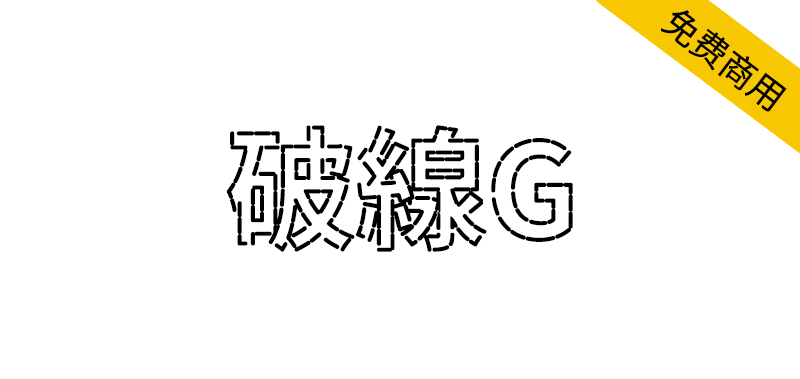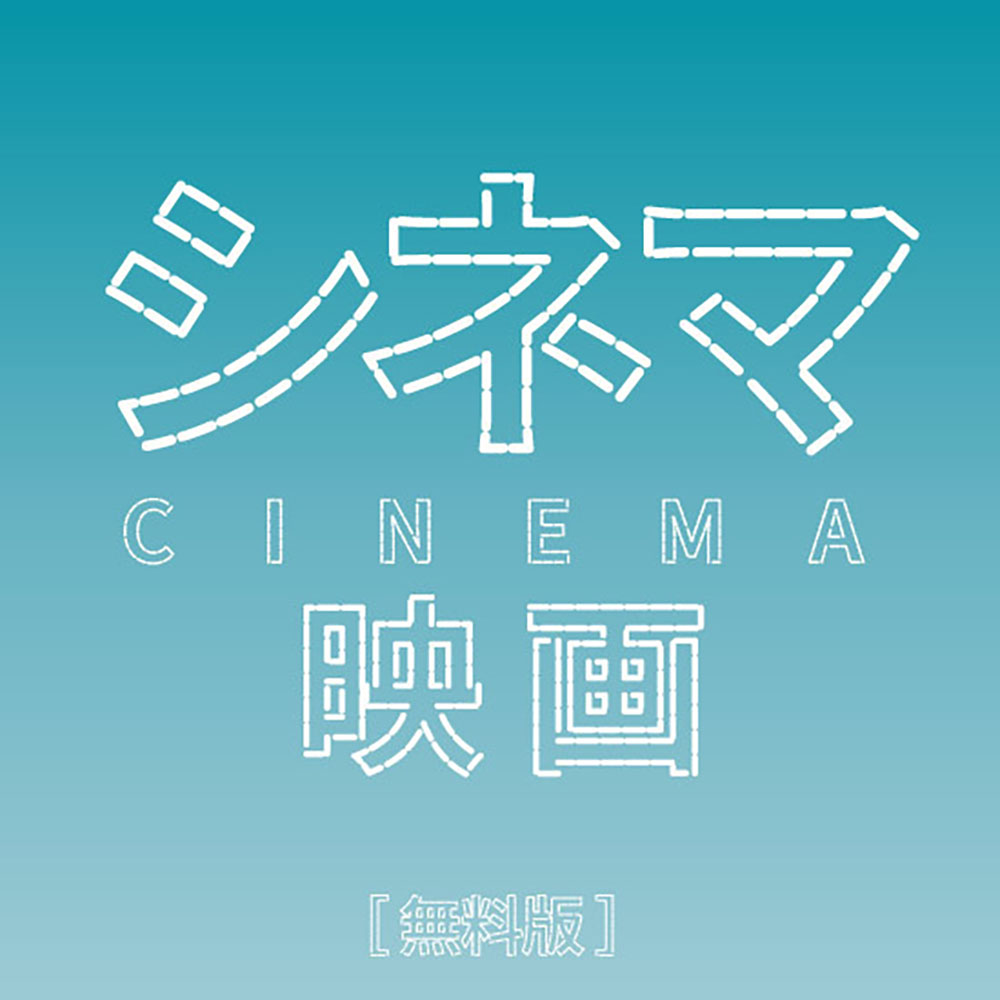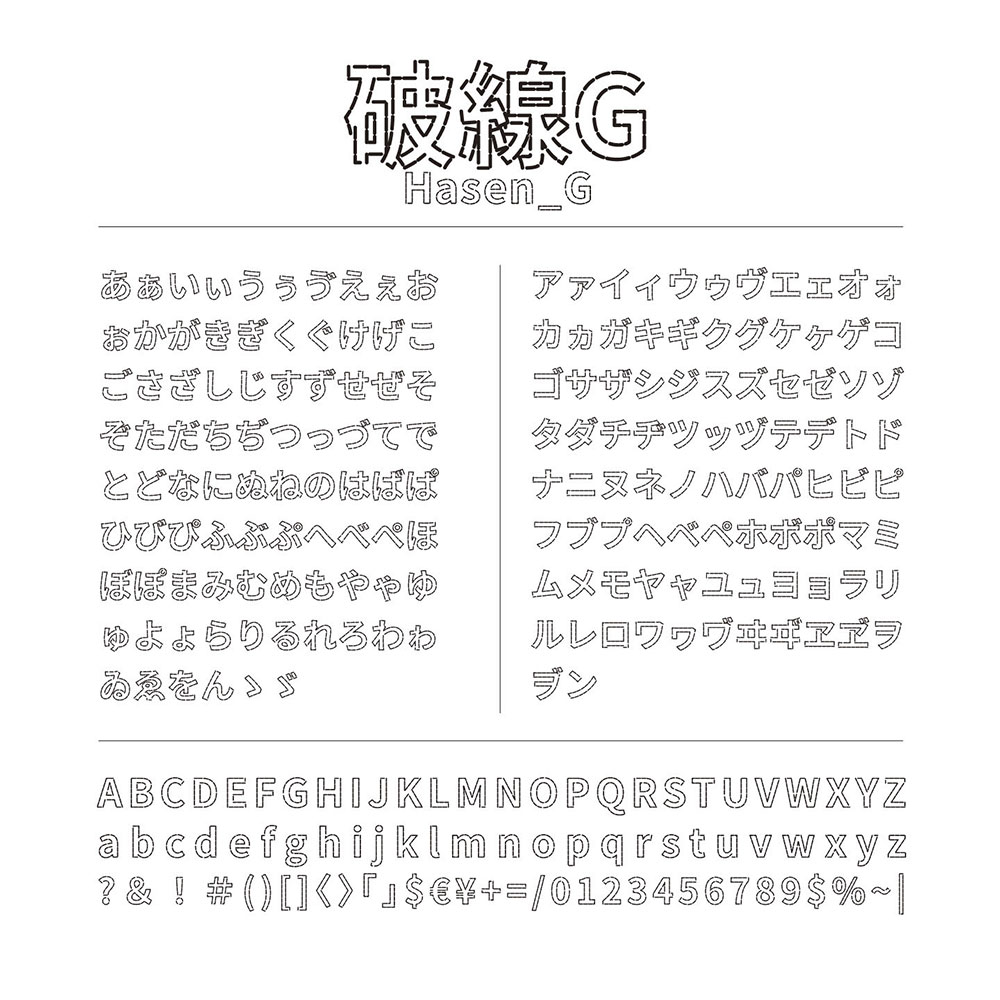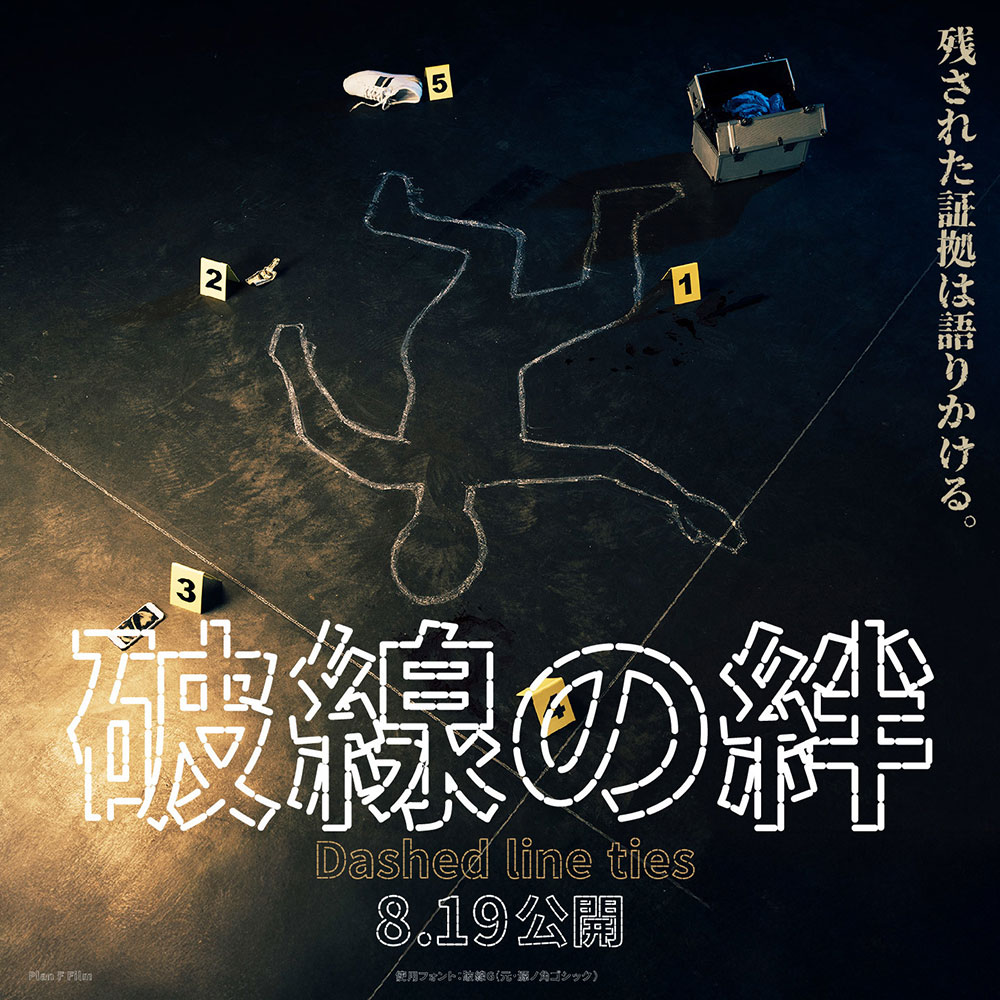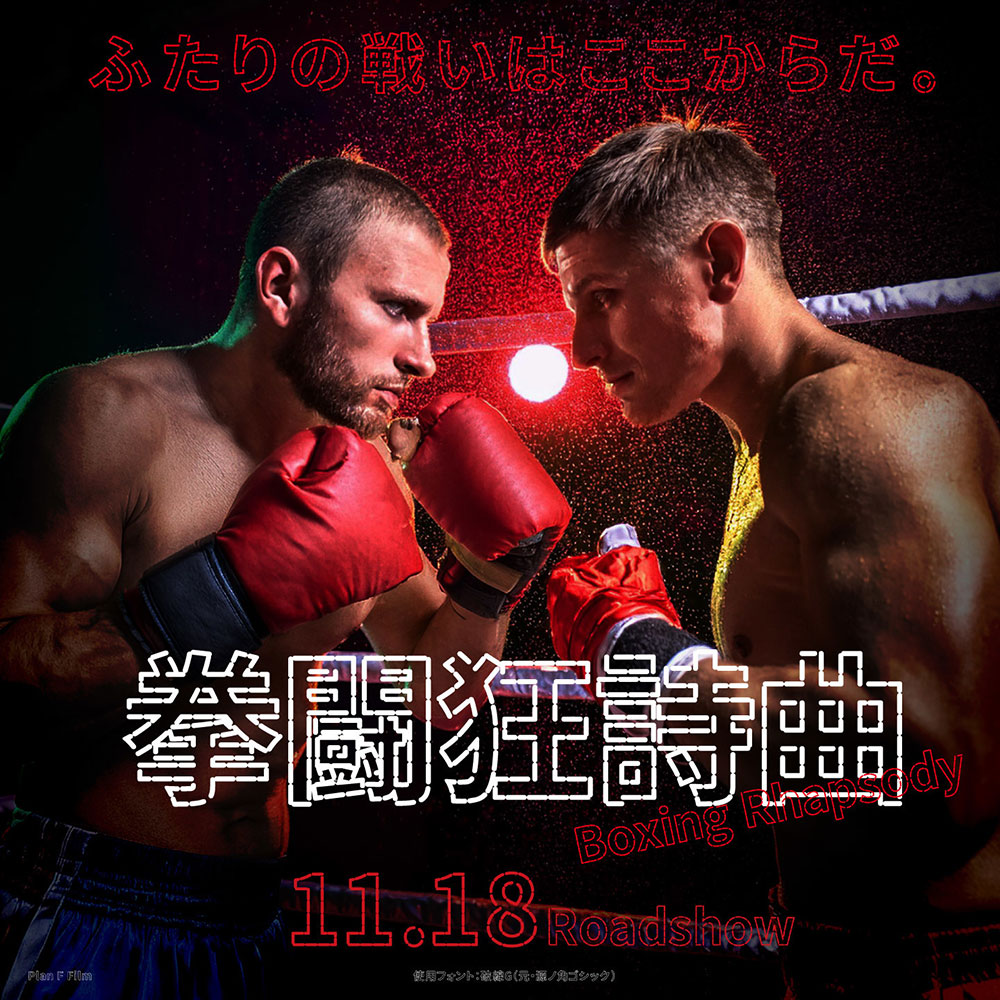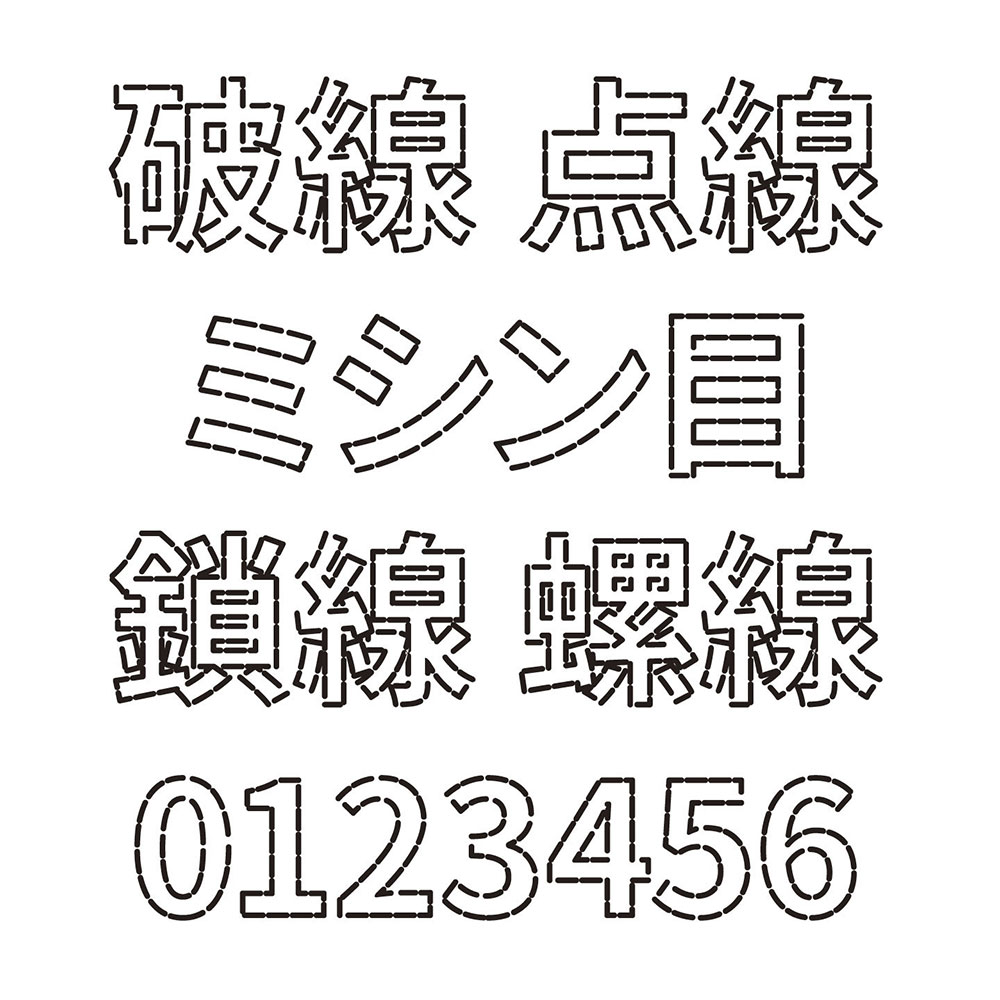
破線G是一款基于思源黑体的用线段组成的创意黑体日文字体,适用于标题,包括二级汉字在内的字符数量约为8,200,它可以免费用于个人用途和商业项目。
破線G 無料版。源ノ角ゴシックをGlyphsソフトのフィルターで加工、ミシン目の縁取りに仕上げました。見出しに便利な日本語フリーフォントです。第二水準漢字を含む文字数は約8200字。私用・商用に無償でお使いいただけます。
破線G是一款基于思源黑体的用线段组成的创意黑体日文字体,适用于标题,包括二级汉字在内的字符数量约为8,200,它可以免费用于个人用途和商业项目。
破線G 無料版。源ノ角ゴシックをGlyphsソフトのフィルターで加工、ミシン目の縁取りに仕上げました。見出しに便利な日本語フリーフォントです。第二水準漢字を含む文字数は約8200字。私用・商用に無償でお使いいただけます。